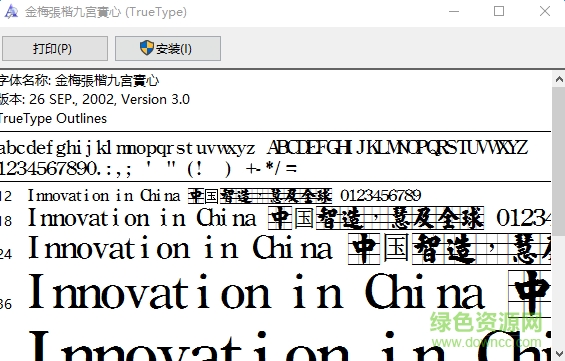
金梅張楷九宮實(shí)心字體是金梅字庫(kù)中很有特色的一款電腦字體,這款字體寫出來的字全部都是實(shí)心的,而且字體比較粗,但是依舊很好看,用于書本印刷、藝術(shù)設(shè)計(jì)都是可以的,歡迎大家來綠色資源網(wǎng)下載。
金梅張楷九宮實(shí)心字體確實(shí)是一款很不錯(cuò)的電腦字體,寫出來的字大氣美觀,而且是越看越好看,大家也可以試試看哦。